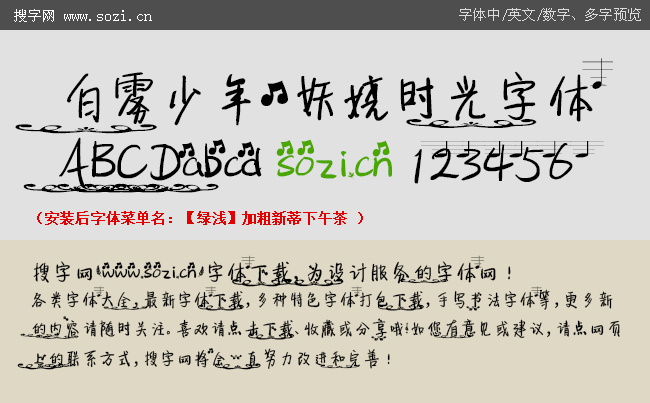
白霧少年@妖嬈時(shí)光字體
搜字網(wǎng)給大家提供一款書法風(fēng)格的字體下載。修改者給他起名為白霧少年@妖嬈時(shí)光字體,這款手機(jī)字體是以新蒂下午茶字體為原形,將字體間插入了大量音符圖案進(jìn)行裝飾,新蒂下午茶字體是一款手寫風(fēng)格的中文簡體字體,非常有手寫感,加入裝飾后更加可愛,喜歡的朋友可下載收藏。